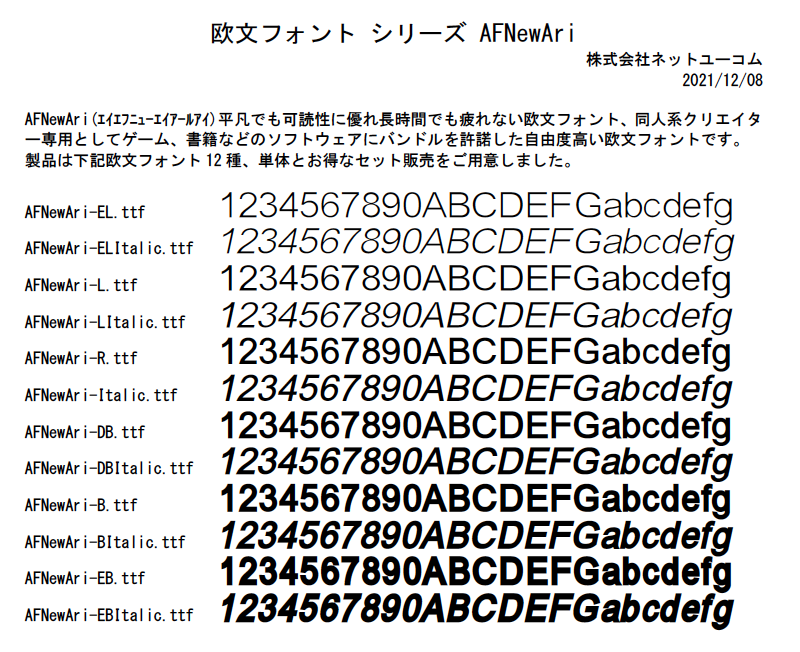
【収録書体】
本商品は下記12書体のセットです。
AFNewAri-ExtraLight
AFNewAri-ExtraLightItalic
AFNewAri-Light
AFNewAri-LightItalic
AFNewAri-Regular
AFNewAri-Italic
AFNewAri-DemiBold
AFNewAri-DemiBoldItalic
AFNewAri-Bold
AFNewAri-BoldItalic
AFNewAri-ExtraBold
AFNewAri-ExtraBoldItalic
AFNewAri(エイエフニューエイアールアイ)は、平凡でも可読性に優れ長時間でも疲れない欧文フォント、同人系クリエイター専用としてゲーム、書籍などのソフトウェアにバンドルを許諾した自由度高い欧文フォントです。